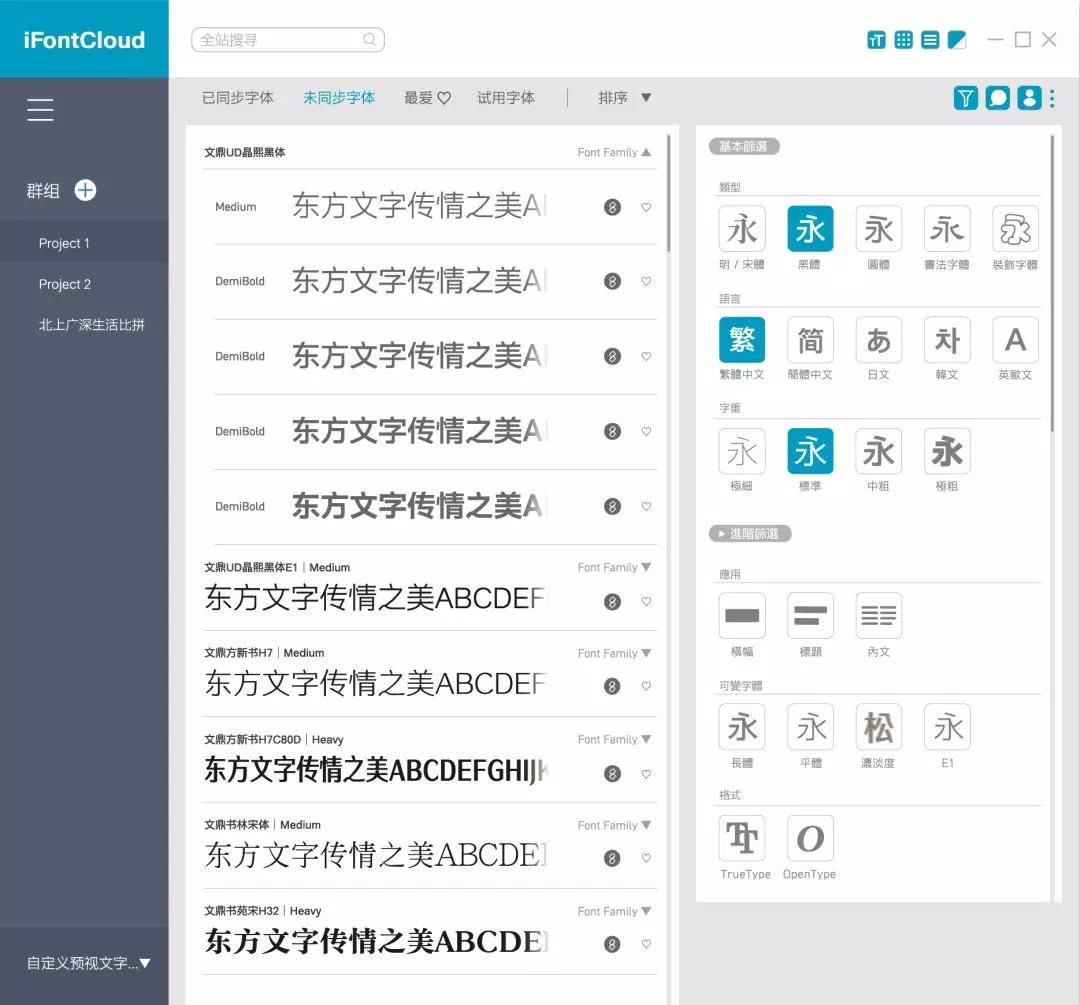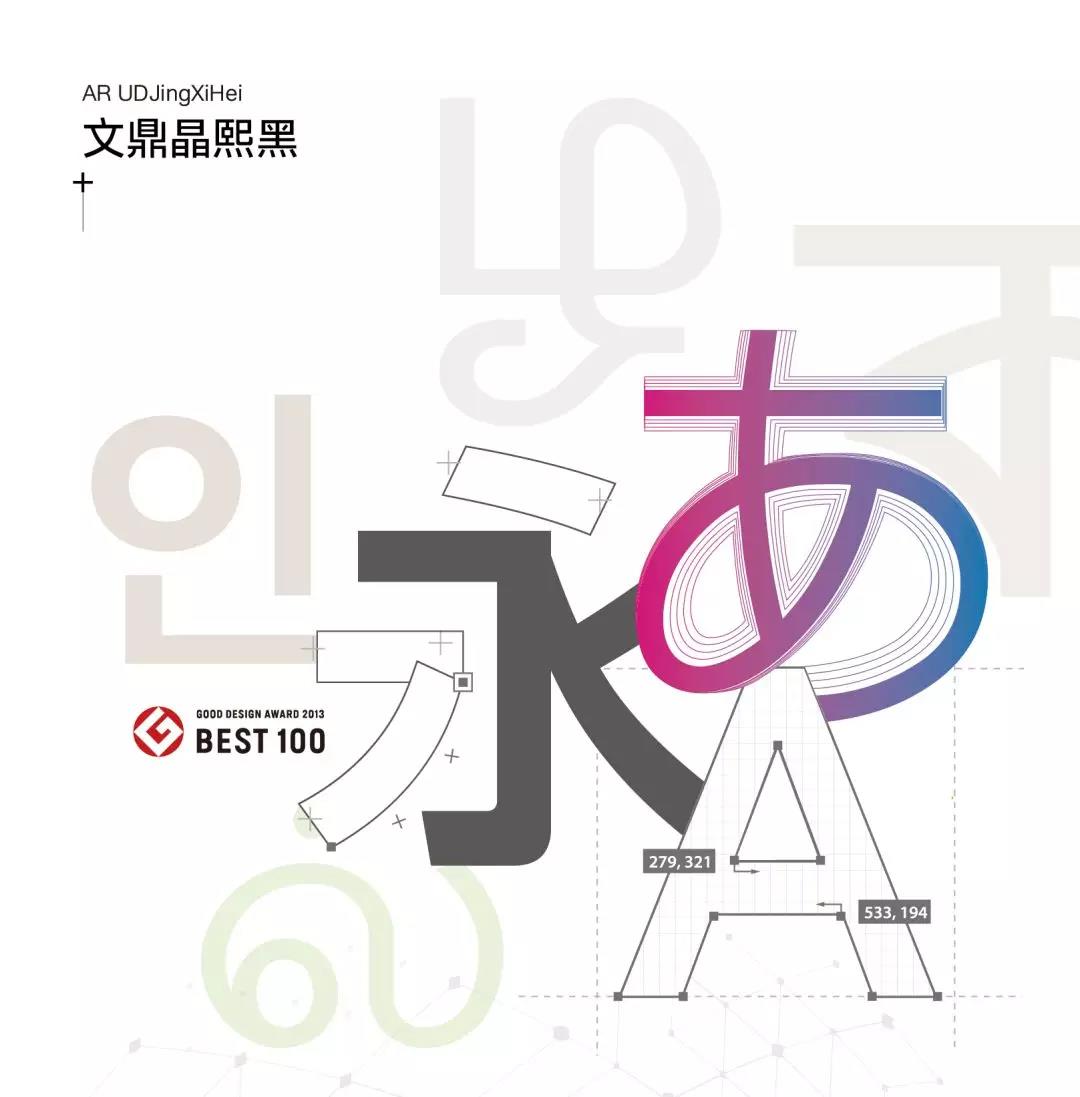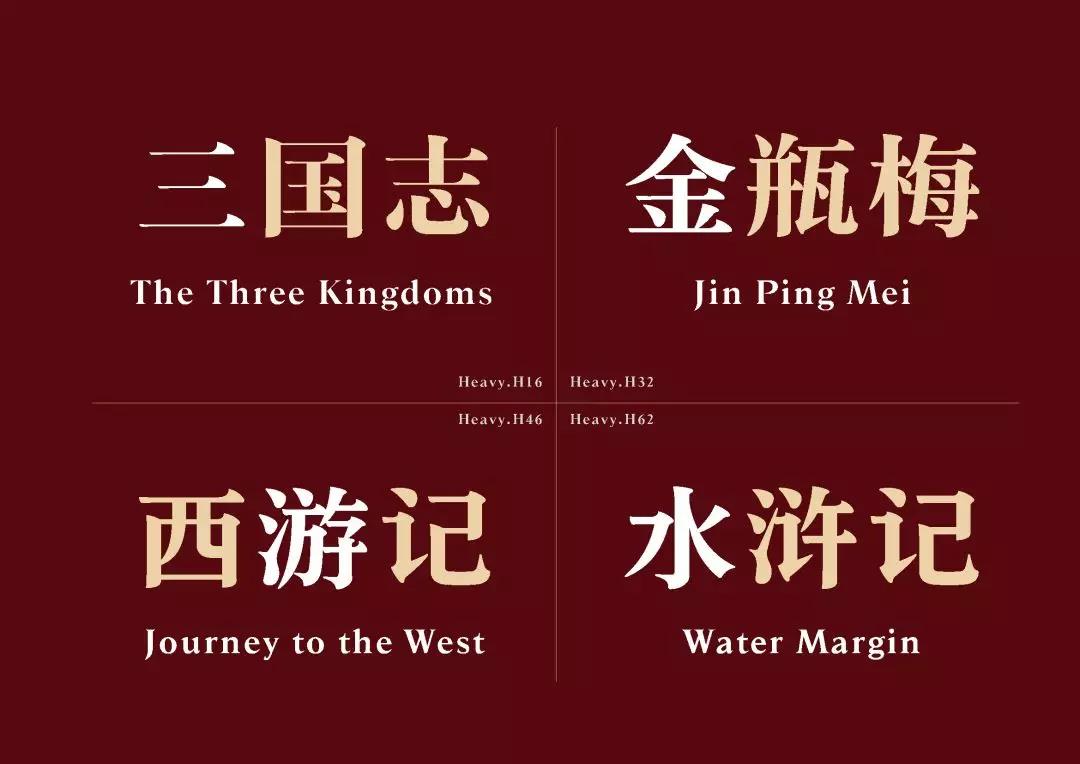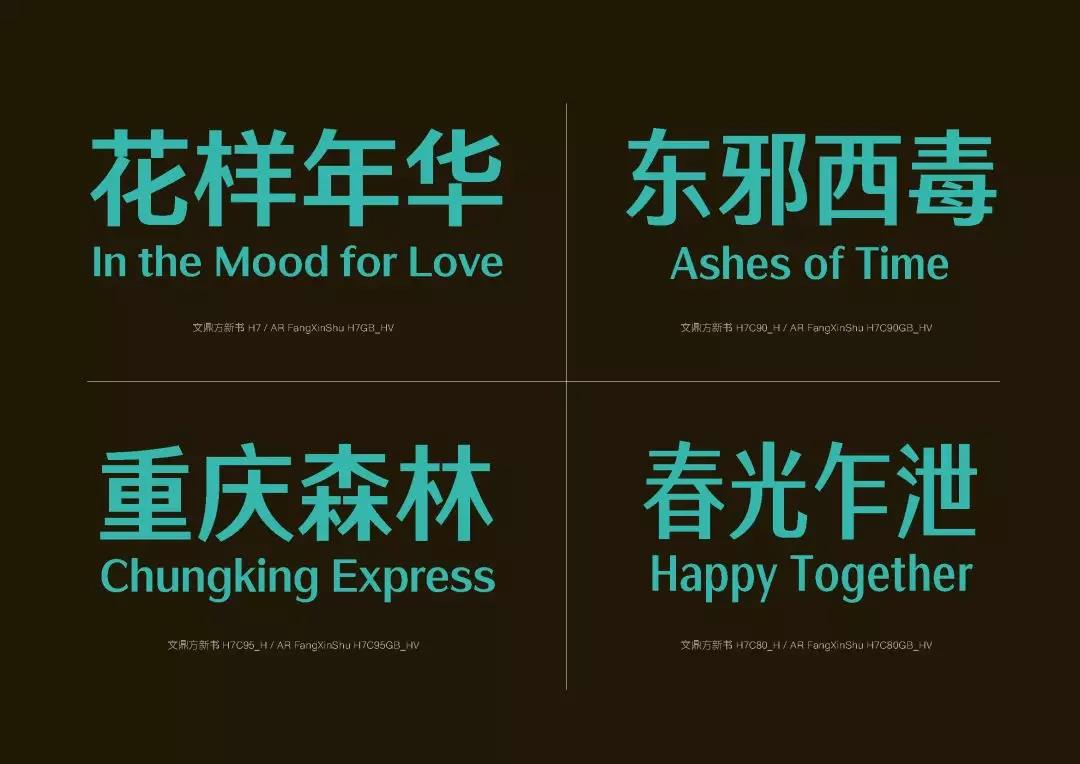
文鼎字库凭借着丰富的经验与优秀团队,致力于字体的设计,成立将近30年来,设计了上百套中文、西文、日文、韩文,以及其他复杂语系等,提供用户最佳的视觉体验效果,明星字体如晶熙黑、方新书与书苑宋等,更得到许多设计师的采用。
其中,晶熙黑体更荣获日本2013年Good Design Award BEST100设计大奖,其丰富且齐全的字重,开创全球语系文字整合设计,以简洁流畅、风格统一及高视觉延展性设计,融入识别性与易读性;更成为全球首款可支持可变字体规格(OpenType 1.8)的中文字体。
文鼎方新书,造型设计修饰了黑体的浑厚视觉感受,融入轻柔优雅的设计,但仍保有黑体的简约平稳风格,彷佛清风吹过般的收笔如眉,呈现出一种轻盈视觉感受,并获得国际字体设计大赛(Granshan International Type Design)的肯定。
因应中文电子阅读趋势与高分辨率、多萤并存需求,必须有新设计来满足新硬件发展的需求,因此「文鼎书苑宋」设计是挽救高阅读性的宋体字逐渐被黑体字体取代的危机,并加以提升阅读速度与明显辨识的视觉传达概念为设计标的。2015年,从来自世界各地数千件的作品中脱颖而出,获得「金点设计奖年度最佳设计奖」。